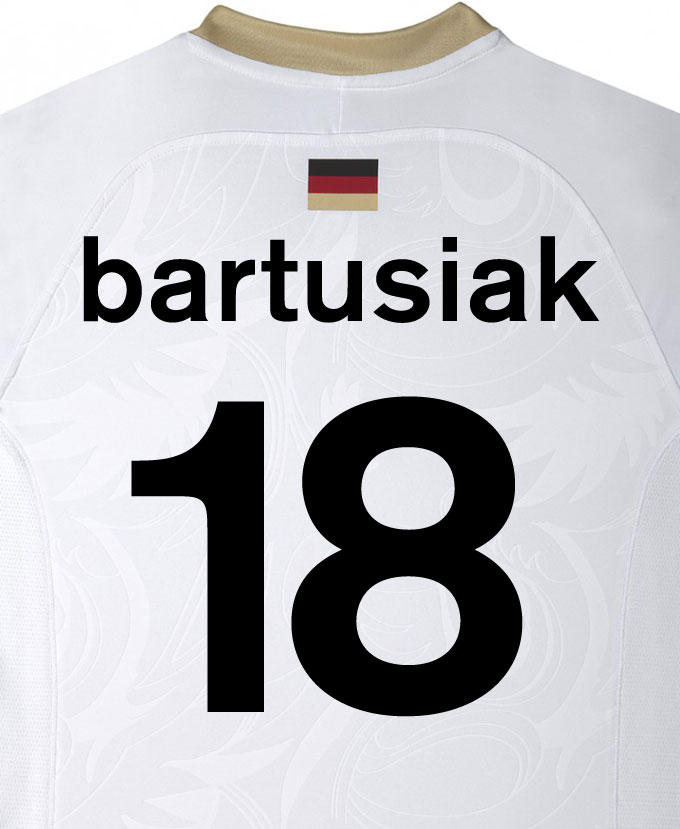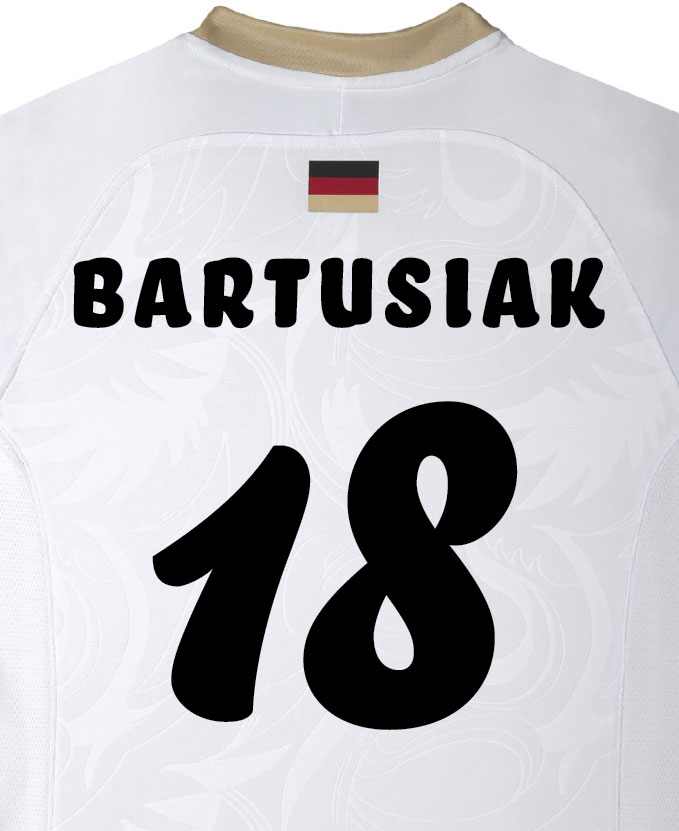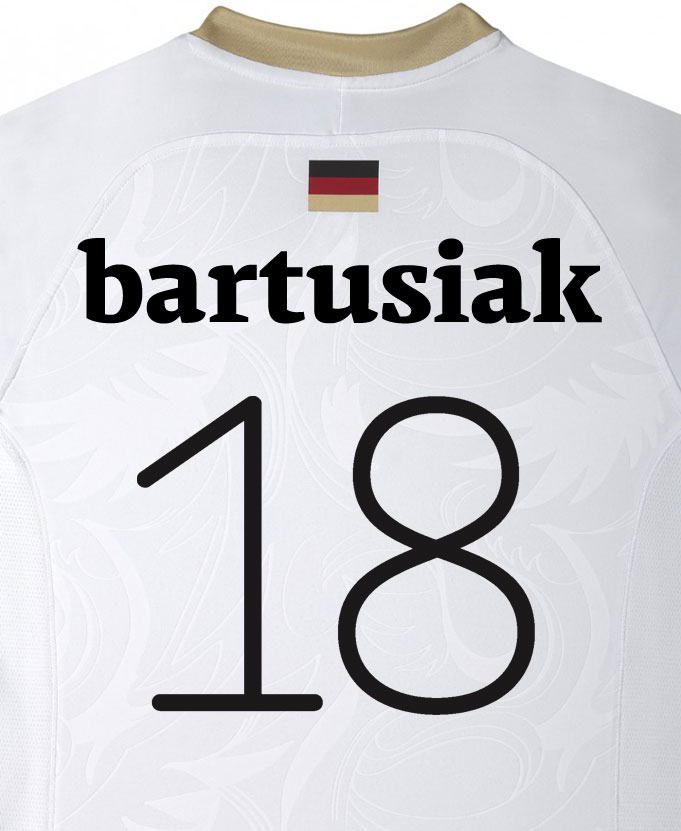
… wir übernehmen die Kosten. Wir, das sind Edenspiekermann (Design) und FontShop (Schriften). Wie zehntausende deutscher Fußball-Fans sind wir der Ansicht, dass die Comic-Schrift auf den Trikots unserer Weltmeister-Frauen keine gute Visitenkarte für Deutschland abgibt. Die Kommentare im Internet sprechen Bände, eine Kostprobe liefert diese Diskussion im Fontblog von letzter Woche.
Wir waren am Wochenende nicht untätig und haben mit einem Team von Designerinnen und Designer rasch drei Alternativen entwickelt – was eben so möglich ist, ohne Briefing und in kürzester Zeit: eine kontrastreiche (Entwurf 1), eine verspielte (Entwurf 2) und eine zeitlos-moderne (Entwurf 3). Laden Sie einfach die vorbereiteten PDF-Dateien unter den nachfolgenden Abbildungen, plotten sie diese auf einen Farbträger Ihrer Wahl und lassen Sie bitte unsere Mädels schon im Viertelfinale grafisch ansprechend ins Stadion einlaufen. Danke.
[Update: Bevor einen der Kommentatoren noch ein Herzkasperl ereilt … möchte ich gerne präzisieren. Die 3 Entwürfe stehen nicht im Wettbewerb zueinander, sondern vertreten jeweils einen typischen Ansatz vertritt (man könnte dies auch, wenn man es zulässt, aus den beiden Absätzen oben herauslesen). Es kann bei dieser Akrion nicht darum gehen, alle Funktionen zu erfüllen. Die Entwürfe sind weder im Fernsehen noch auf einem Rücken getestet worden. Und alle die offenen Fragen (Klein- bzw. Großschreibung, ß oder nicht, Strichstärken, Schriftmischungen) bleiben weiterhin offen, damit sie besprochen werden können. Wir haben uns vorgewagt und verdienen mehr als Nölerei. Zum Glück haben inzwischen einige Kollegen Alternativen veröffentlicht. Danke, noch mal.]
Entwurf 1: Schriften: Markant Extrabold (Design: Claus Eggers), Chevin Thin (Nick Cooke)
Entwurf 2: Schriften: Bello Semibold Caps, Bello Script (Design: Underware)
Entwurf 3: Schrift: Akzidenz Grotesk Medium (Design: H. Berthold AG)
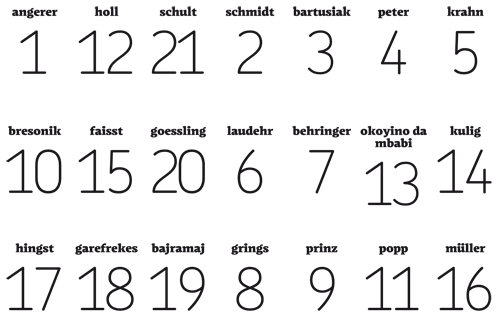
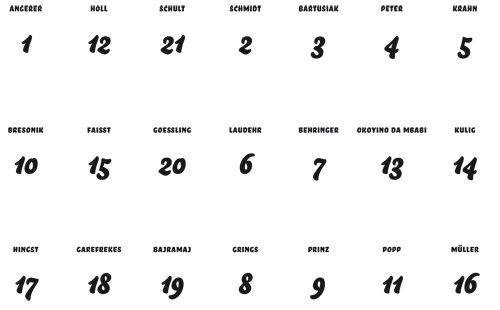
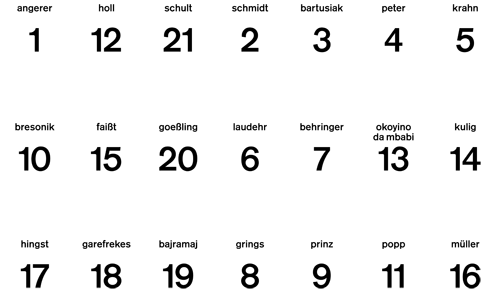
Naja…sind alle drei nicht wirklich überzeugend. Da waren die Vorschläge im letzten Artikel deutlich besser!
Entwurf 3 ist doch kein Alternativ-Vorschlag. Das ist das typische „Designer-selbstverwirklichungs-Ding“. Aufgabe ist doch eine gute „Comic/Script“-Alternative zu bringen.
Bello geht in die richtige Richtung.
Luc de Groot sollte die Font stellen. http://www.lucasfonts.com/
also ich finde das auch eher mittel. #2 ist akzeptabel aber ich verstehe überhaupt nicht warum es eine script-schrift sein soll. finde ich für trikots generell unpassend. die ziffern von #1 (chevin thin) sind sehr schön aber ob man die auf kleinen fernsehern (soll’s ja noch geben) wirklich gut lesen kann wage ich zu bezweifeln.
Die 1. Version finde ich ok. Aber die Zahlen vermitteln kein „stabiles” Gefühl. Eher: Gegner stupse mich an … ich kippe um!
Ein fetterer Schnitt würde die Spielerinnen kompakter erscheinen lassen. Damit meine ich nicht „unweiblich”, „dick” oder ähnliches. Warum überhaupt der Schriftwechsel? V1 ist einfach zu „unmutig”.
(V2 = Kindergarten, V3 = langweile Pur).
Nummer 1 ist doch ein ganz schlechter Scherz, oder? Nummer 2 sieht ebenfalls vermurkst aus und Nummer 3 sieht nach Mediengestalter-Ausbildung zweite Woche aus.
Im Ursprungstrikot-Artikel war doch die Rede von der DIN-Schrift. Warum nicht die?
Die ist stabil und in der Vorstellung auch “typisch deutsch”. Man könnte sie gut auf den Trikots lesen und sie würde ferner trotzdem nicht langweilig aussehen.
Ist natürlich nur meine Meinung, aber ich würd ihr eine Chance geben. Eher als den Entwürfen hier.
Natürlich sind die Entwürfe besser als die Action-Man-Hemden, aber sie sind auch nicht das Gelbe vom Ei. Die Namen dürften in allen drei Entwürfen schlecht erkennbar sein, und die Lesbarkeit der Bello-Ziffern sind auch nicht gerade optimal.
Gut gefallen mir die englischen Trikots:
Dem Schnitt der Trikots trägt keiner dieser Entwürfe Rechnung. Das ergibt einfach kein Zusammenspiel und somit auch keine stimmige Anmutung.
Schöne Aktion. Entwurf # 1 und # 2 gefallen mir gut. Wobei #1 besser als der zweite Entwurf. Aber die Chevin Thin ist nicht ganz sauber gezeichnet/digitalisiert oder? Bei #3 dachte ich erst, dass das Designerteam den Bogen an der „1“ hinzugefügt hat. Aber die AG Medium scheint wirklich so geschnitten zu sein. ;-) Wieder was gelernt. Läuft nur im Regularschnitt gerade in den Stamm.
zu Entwurf 3:
Mir war bisher nie aufgefallen, dass der Medium-Schnitt der Akzidenz Grotesk als einziger die untere Rundung an der 1 hat. Trotzdem ist diese Schrift an sich ungefähr so sportlich-dynamisch wie meine Steuererklärung und damit in meinen Augen komplett fehl am Platz.
… die Egowichserei und das Geltungsbedürfnis einiger Designer geht mir beträchtlich auf den Sack. Einfach irgendeine andere Schrift nehmen und lieblos auf den Trikotrücken klatschen kann ja wohl jeder Praktikant. Hat edenspiekermann das nötig?